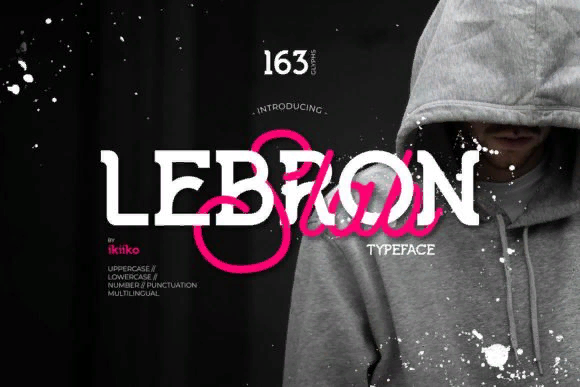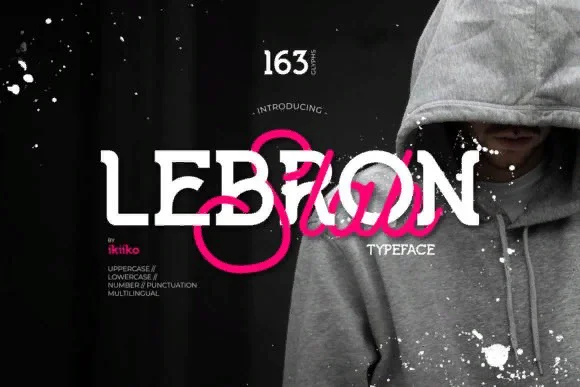
Название: Lebron Font (2021)
Lebron - это смелый и уникальный шрифт с наклонной засечкой.
Этот шрифт имеет внушительный вид, и поэтому он легко подойдет для широкого спектра работ, требующих выразительного штриха.